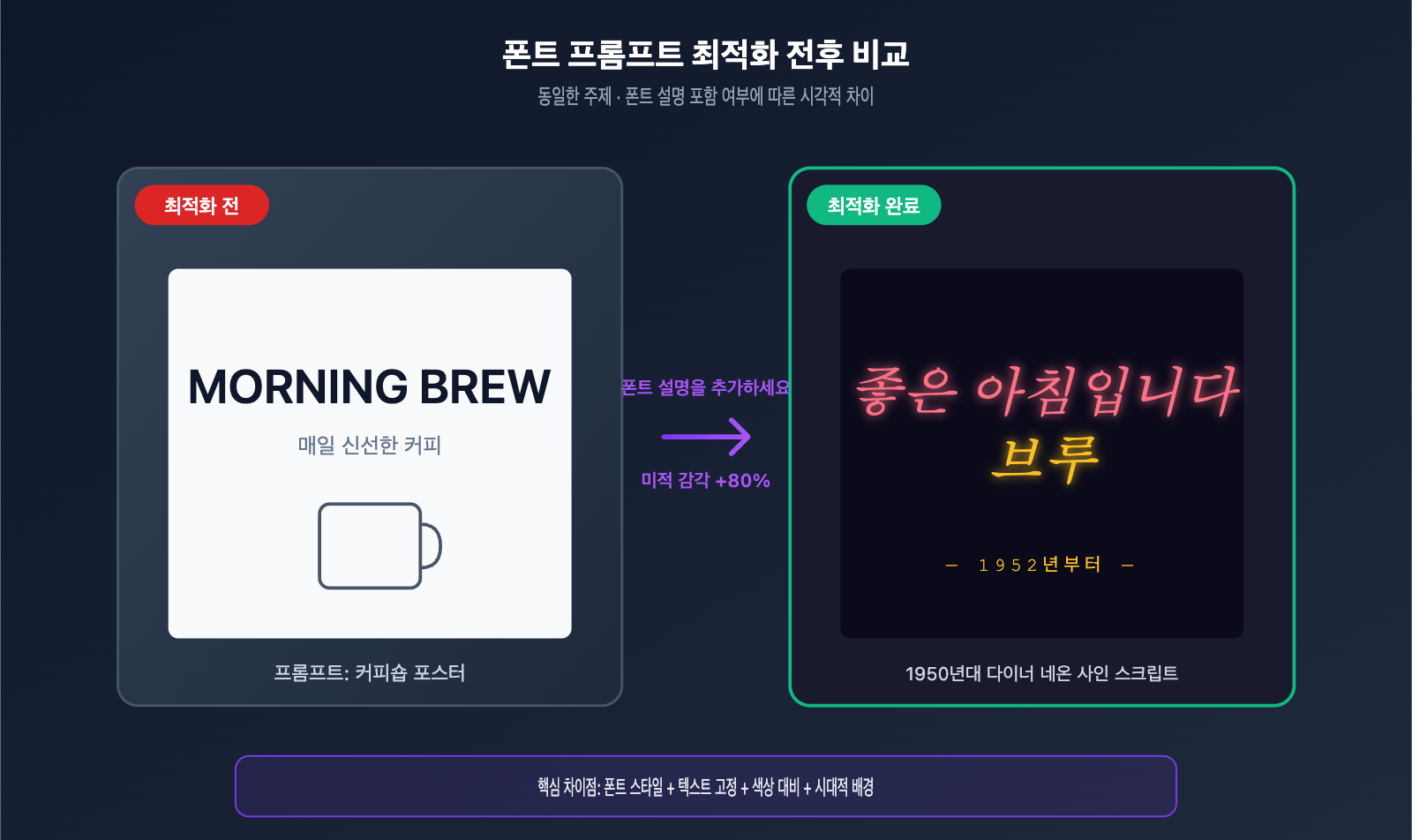
gpt-image-2 API 텍스트-이미지 변환 프롬프트 완벽 가이드: 미적 감각을 80% 향상시키는 6가지 묘사법
많은 사용자가 gpt-image-2 API나 ChatGPT 공식 웹사이트에서 이미지를 생성할 때 공통적으로 겪는 문제가 있습니다. 모델이 생성한 이미지의 텍스트 인식률은 매우 높지만, 폰트가 항상 "엔지니어의 감성"이 느껴지는 평범한 산세리프체로만 나온다는 점이죠. 브랜드 느낌이나 디자인 요소가 부족한 이런 "소박한 미학"은 포스터, SNS 커버, 제품 홍보 이미지를 만들 때 특히 두드러지며, 전체적인 구도가 좋아도 결과물을 저렴해 보이게 만듭니다.
문제의 근본 원인은 모델의 성능 부족이 아니라, 대부분의 사용자가 프롬프트에 "무엇을 그릴지"만 설명하고 "폰트가 어떤 모양이어야 하는지"는 알려주지 않았기 때문입니다. 이 글에서는 OpenAI 공식 Cookbook과 여러 API 서비스 업체의 실측 경험을 바탕으로 gpt-image-2 폰트 프롬프트의 작동 메커니즘을 체계적으로 분석합니다. 바로 사용할 수 있는 6가지 폰트 설명 템플릿을 제공하고, APIYI(apiyi.com) 플랫폼의 모델 호출 예시를 결합하여 5분 안에 미적 감각이 살아있는 폰트 프롬프트 작성법을 알려드립니다.
1. gpt-image-2 폰트 프롬프트의 핵심 메커니즘
1.1 왜 기본 폰트는 항상 평범한 산세리프체일까?
gpt-image-2는 명확한 폰트 설명이 없으면 학습 데이터에서 "가장 안전한" 시각적 우선순위에 따라 폰트를 생성합니다. 그 결과는 대개 중립적인 기하학적 산세리프체(Inter, Helvetica 스타일과 유사)가 되며, 이는 인식률은 보장하지만 스타일리시한 표현은 희생하게 됩니다.
OpenAI 공식 프롬프트 가이드에 따르면, 모델은 사용자가 능동적으로 제약한 시각적 속성만 렌더링하며, 제약이 없는 부분은 모두 기본값으로 처리합니다. 즉, "커피에 관한 포스터"라고만 쓰면 모델은 가장 평범한 폰트를 선택합니다. "굵은 붓 터치가 있는 손글씨 스타일의 세리프체(hand-lettered display serif with thick brushstrokes)"처럼 상세하게 적어야만 모델이 그에 맞는 폰트 우선순위를 적용합니다.
이것이 바로 같은 주제와 프롬프트 길이라도 폰트 설명 유무에 따라 결과물의 퀄리티가 한 단계 차이 나는 이유입니다. 이 점을 이해하면 "폰트가 평범하다"는 것은 모델의 결함이 아니라, 사용자가 폰트를 이미지의 핵심 정보로 설명하지 않았기 때문임을 알 수 있습니다.
또 하나 간과하기 쉬운 요소는 모델 버전입니다. gpt-image-2는 1.5세대 대비 가장 큰 업그레이드가 텍스트 렌더링 레이어에서 이루어졌습니다. 최대 4K 출력을 기본 지원하며, 작은 글씨, 밀집된 레이아웃, 다중 폰트 혼용 처리 능력이 크게 향상되었습니다. 이는 곧 gpt-image-2에서 폰트 프롬프트에 투자하는 시간만큼의 보상이 확실하다는 뜻이기도 합니다.
1.2 gpt-image-2 폰트 프롬프트의 4가지 핵심 요소
"폰트 설명"을 분해해 보면, gpt-image-2는 다음 4가지 독립적인 차원의 명령에 반응합니다. 하나라도 빠지면 안 됩니다.
요소 역할 설명 예시
폰트 스타일 (Style) 자형 구조와 시각적 성격 결정 굵은 산세리프, 압축된 세리프, 손글씨 스타일
폰트 계층 (Hierarchy) 제목/부제목/본문의 대비 조절 큰 제목, 작은 본문
색상 대비 (Contrast) 폰트와 배경의 가독성 결정 네이비 배경에 흰색 글씨 등 높은 대비
공간 레이아웃 (Placement) 텍스트 위치와 정렬 방식 고정 상단 중앙 배치, 깔끔한 자간
1.3 텍스트를 고정하는 강력한 제약 작성법
OpenAI Cookbook의 image-gen-models-prompting-guide는 중요한 팁을 하나 제공합니다. 화면에 나타날 문자열을 따옴표나 대문자로 감싸면, 모델은 이 부분을 "반드시 그대로 렌더링해야 하며, 글자가 추가되거나 틀려서는 안 되는" 강력한 제약으로 이해합니다.
실제로 테스트해 보면 the word coffee on a sign이라고 쓰는 것보다 a sign with the EXACT text "COFFEE"라고 쓰는 것이 철자 오류 확률이 훨씬 낮으며, 후자는 거의 완벽하게 문자 수준의 일관성을 보장합니다. 철자가 어려운 브랜드 이름(예: Schønne, APIYI)은 "A P I Y I"와 같이 공백을 넣어 한 글자씩 적어주면 글자 깨짐 위험을 더욱 줄일 수 있습니다.
2. gpt-image-2 폰트 프롬프트 실전 작성법 6가지
상황에 따라 적절한 폰트 묘사 전략이 다릅니다. 아래 6가지 방법은 OpenAI 공식 예제, fal.ai 실전 사례, 그리고 오픈 소스 프롬프트 라이브러리에서 정리한 자주 쓰이는 재사용 가능한 템플릿입니다.
2.1 기능 묘사법: 가장 안정적인 기초 작성법
타이포그래피 전문 용어를 사용하여 글자 형태를 직접 묘사하는 방식입니다. OpenAI에서 가장 권장하는 방법이며, 성공률이 가장 높습니다.
• bold geometric sans-serif (두꺼운 기하학적 산세리프, IT 브랜드에 적합)
• condensed sans-serif with tight tracking (좁은 폭의 산세리프, 잡지 제목에 적합)
• classic transitional serif with fine hairlines (정교한 세리프, 명품/출판물에 적합)
• rounded humanist sans-serif (둥근 휴머니스트 산세리프, 어린이/친근한 브랜드에 적합)
2.2 스타일 및 감성 묘사법: 폰트에 "성격" 부여하기
구체적인 폰트 이름 대신 예술 사조나 디자인 스타일을 사용하여 모델이 전체 미학 체계를 이해하도록 유도합니다.
• minimalist Bauhaus sans-serif
• Art Deco display typography with metallic strokes
• brutalist concrete typography
• Memphis-style 80s display font with bold geometric shapes
이 방식의 장점은 폰트가 따로 놀지 않고, 모델이 그에 어울리는 색상, 레이아웃, 장식 요소를 자동으로 매칭하여 전체적인 디자인 언어가 훨씬 통일감 있게 완성된다는 점입니다.
2.3 시대적 배경 묘사법: 향수를 불러일으키는 미학 재현
시대와 매체를 조합하여 특정 역사적 시기의 실제 인쇄물에서 스캔한 듯한 느낌을 줍니다.
• 1970s vinyl record cover psychedelic display font
• 90s grunge zine handwritten typography with photocopy texture
• early 2000s Y2K chrome bubble font
• 1950s diner neon sign script lettering
시대적 배경 묘사법은 복고풍, 빈티지, 서브컬처 테마의 커버를 생성할 때 특히 유용하며, 단순히 retro font라고 쓰는 것보다 정확도가 훨씬 높습니다.
2.4 브랜드 분위기 묘사법: 상업용 이미지 제작의 첫 번째 선택
목표 산업의 시각적 분위기를 직접 묘사하여 모델이 성숙한 상업용 폰트 규격에 맞춰 생성하도록 합니다.
• editorial fashion magazine serif typography, Vogue style
• tech startup landing page typography, clean and confident
• luxury skincare branding typography, refined and minimal
• craft brewery label typography, hand-drawn rustic feel
2.5 물리적 재질 묘사법: 폰트를 "입체적 존재"로 만들기
폰트를 단순한 디지털 레이어가 아닌 현실 세계의 물리적 객체로 간주하는 방식입니다. fal.ai 튜토리얼에서 강조하는 고급 기법입니다.
• plastic letter board with uneven letter spacing, one missing slot
• glowing neon tube letters with visible glass tubing and cables
• cut paper letters with soft drop shadows, layered cardboard
• chiseled marble inscription with deep shadow inside the cuts
물리적 재질을 묘사하면 폰트에 자연스러운 빛, 그림자, 마모 디테일이 더해져 평면적인 텍스트보다 훨씬 뛰어난 질감을 보여줍니다.
2.6 참고 폰트 이름 활용법: 특정 서체 재현
OpenAI 공식적으로 지원하는 폰트 화이트리스트는 없지만, 테스트 결과 유명한 폰트 이름은 인식되는 경우가 많습니다. 기능 묘사 뒤에 보조 수식어로 붙이면 효과가 좋습니다.
폰트는 이미지의 장식이 아니라 이미지의 영혼입니다. gpt-image-2 폰트 프롬프트 작성법을 익히는 것은, 본질적으로 '프롬프트 엔지니어링'의 영역을 화면 구도에서 타이포그래피 디자인으로 확장하는 것이며, 이는 AI 이미지 생성이 '볼만한 수준'에서 '전문가 수준'으로 도약하는 핵심 열쇠입니다.